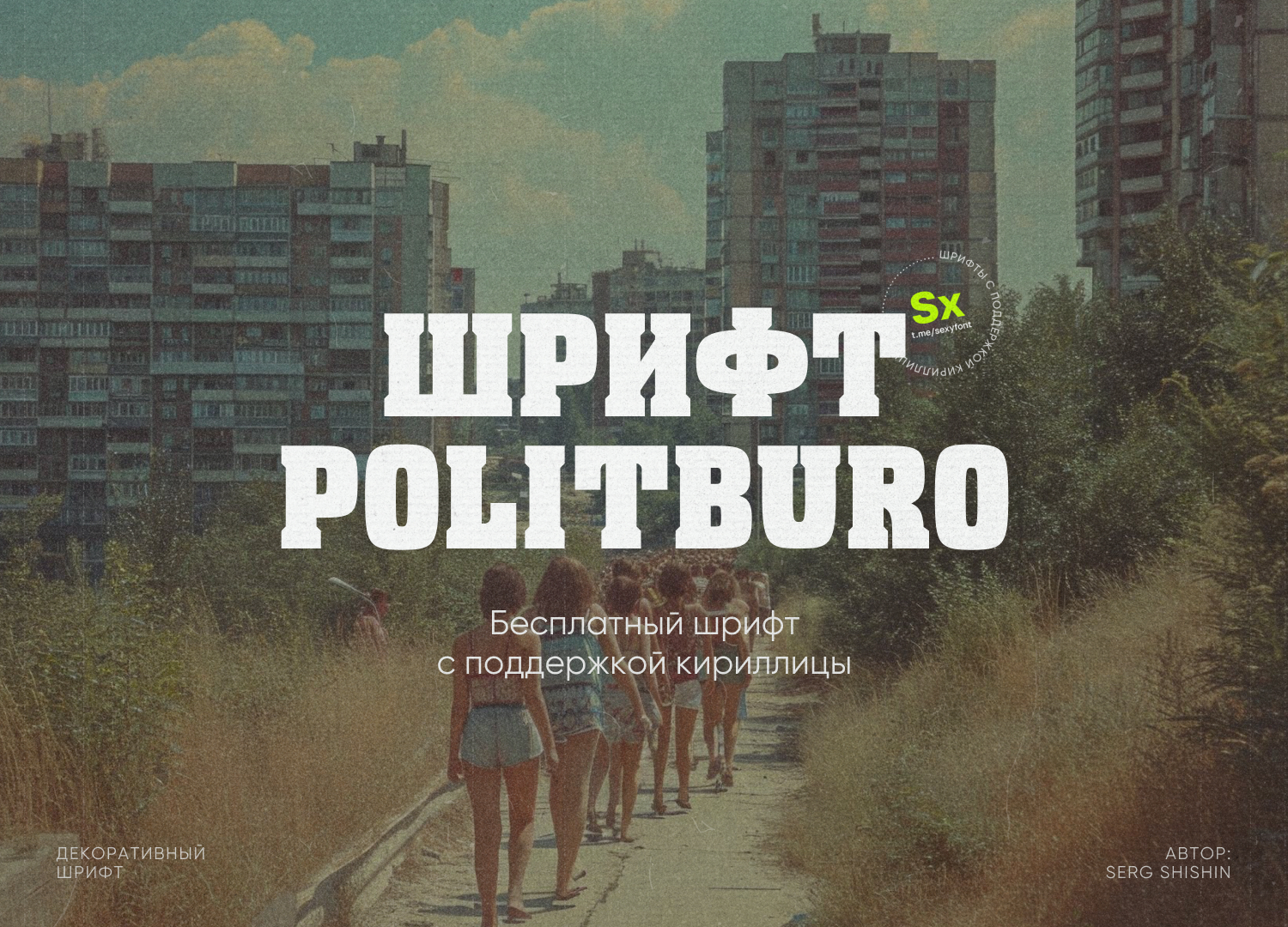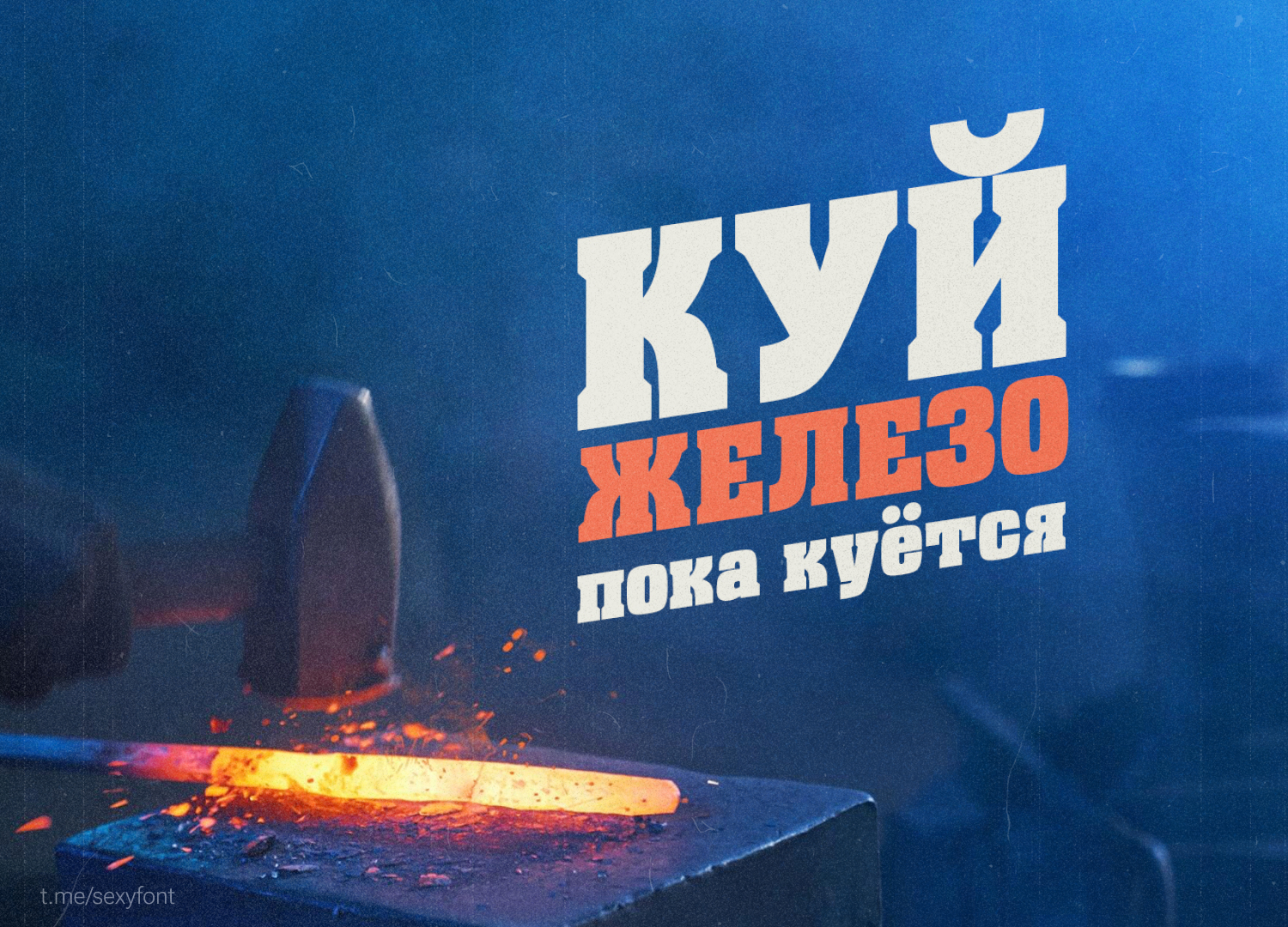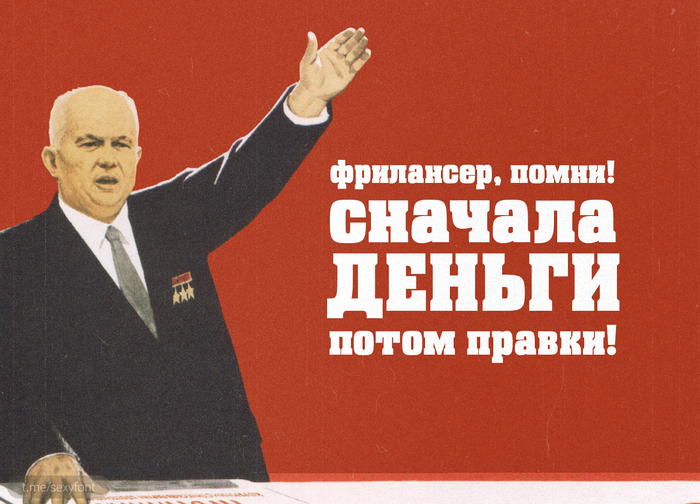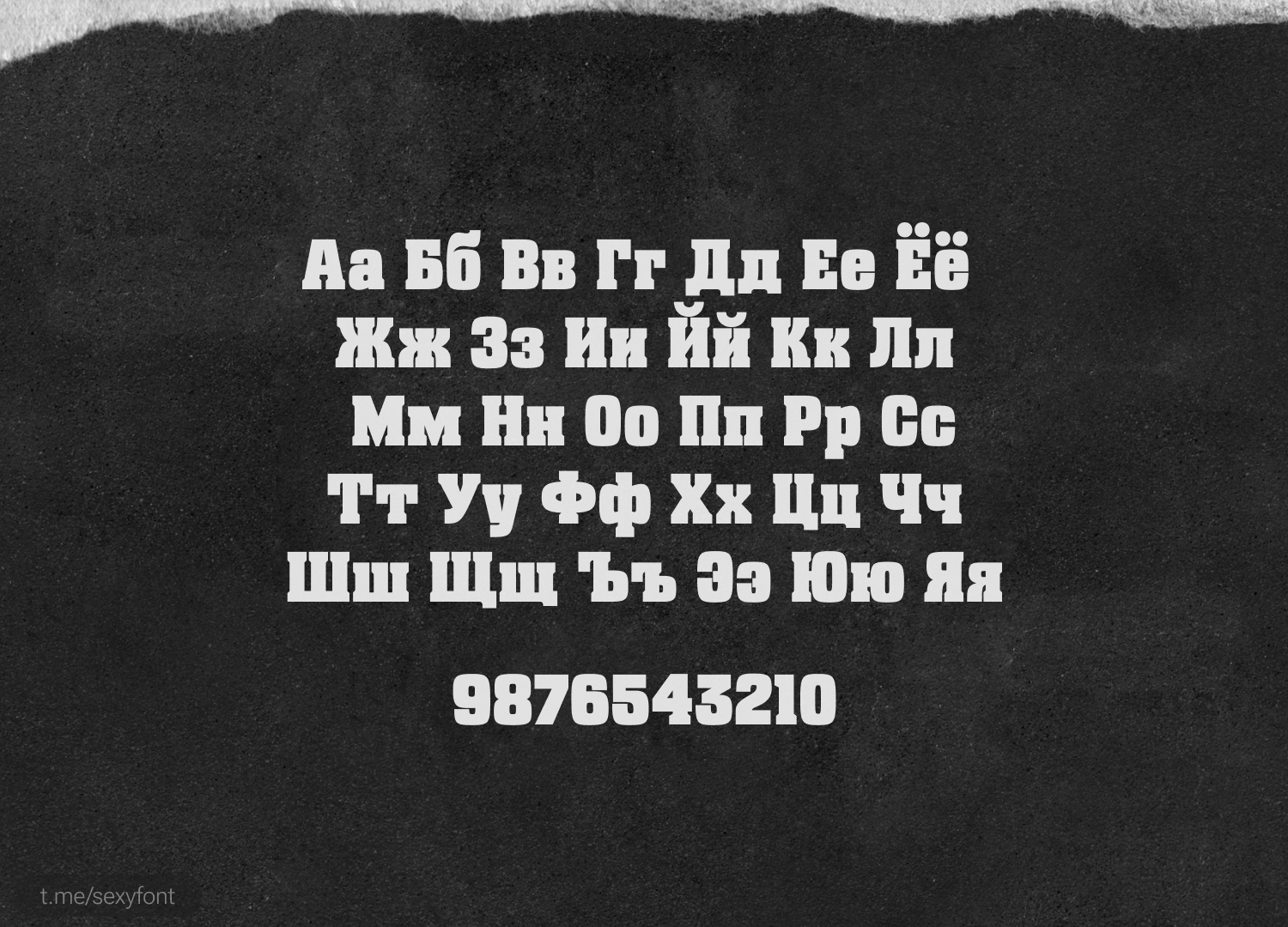
Шрифт Politburo
Мощный, предельно выразительный плакатный шрифт, для воплощения ваших самых смелых творческих идей! Распространяется полностью бесплатно.
Автор: Sergey Shishin